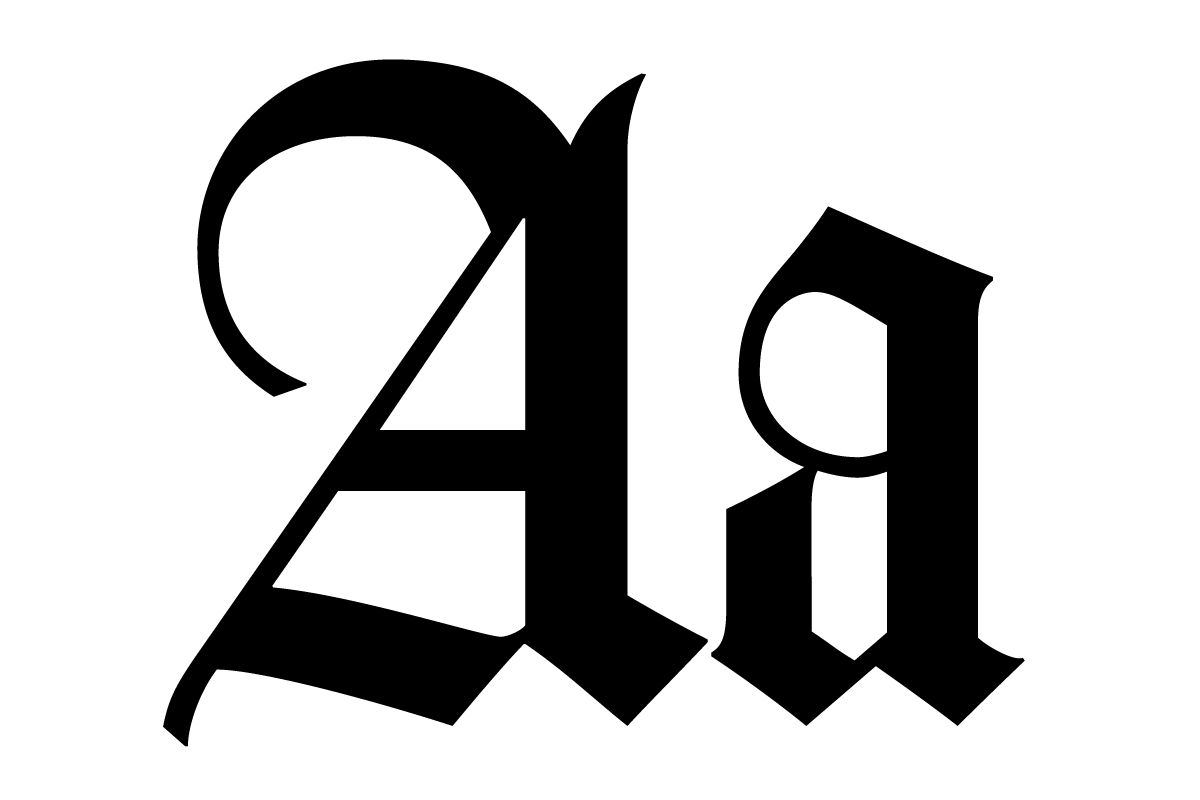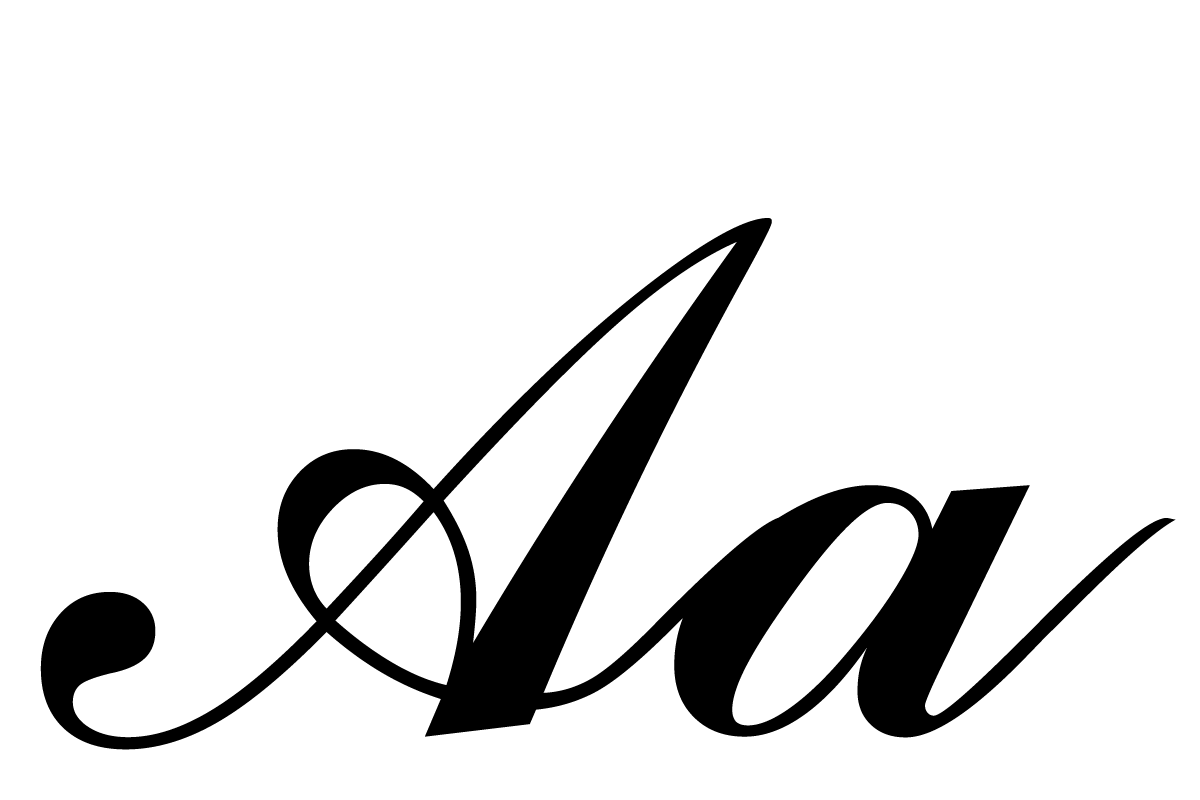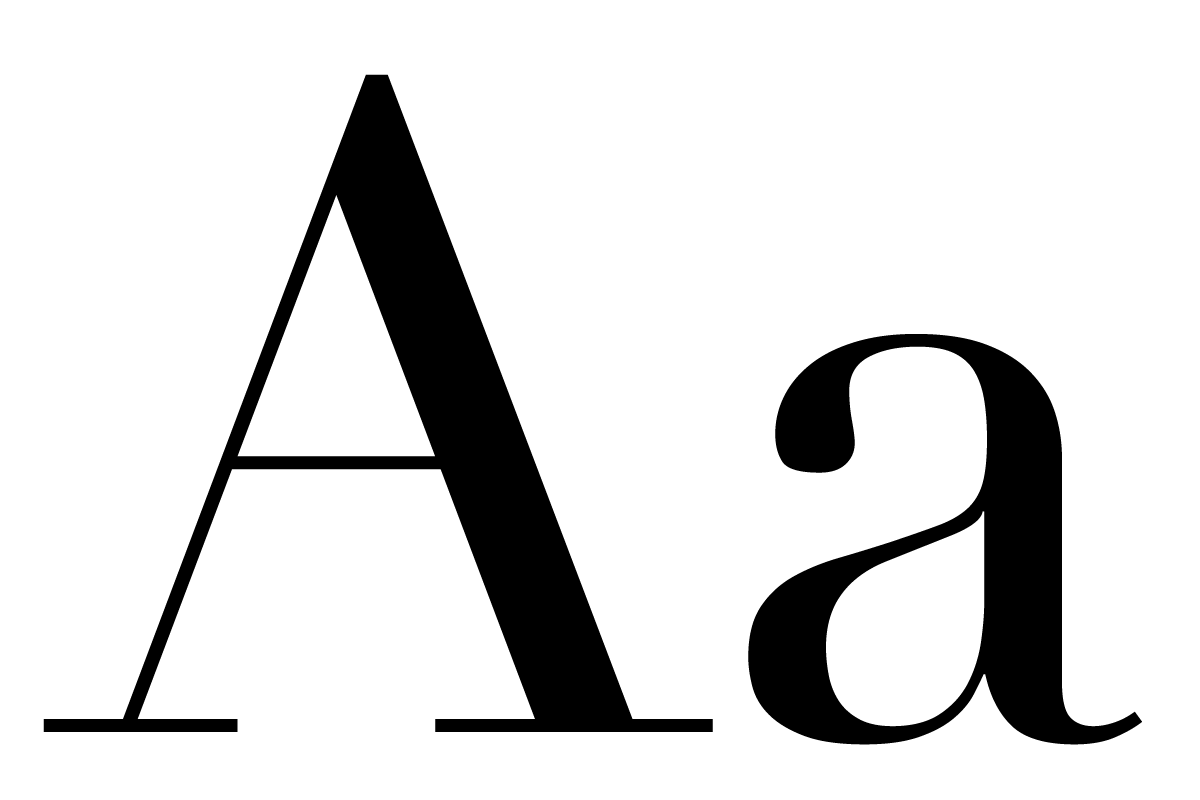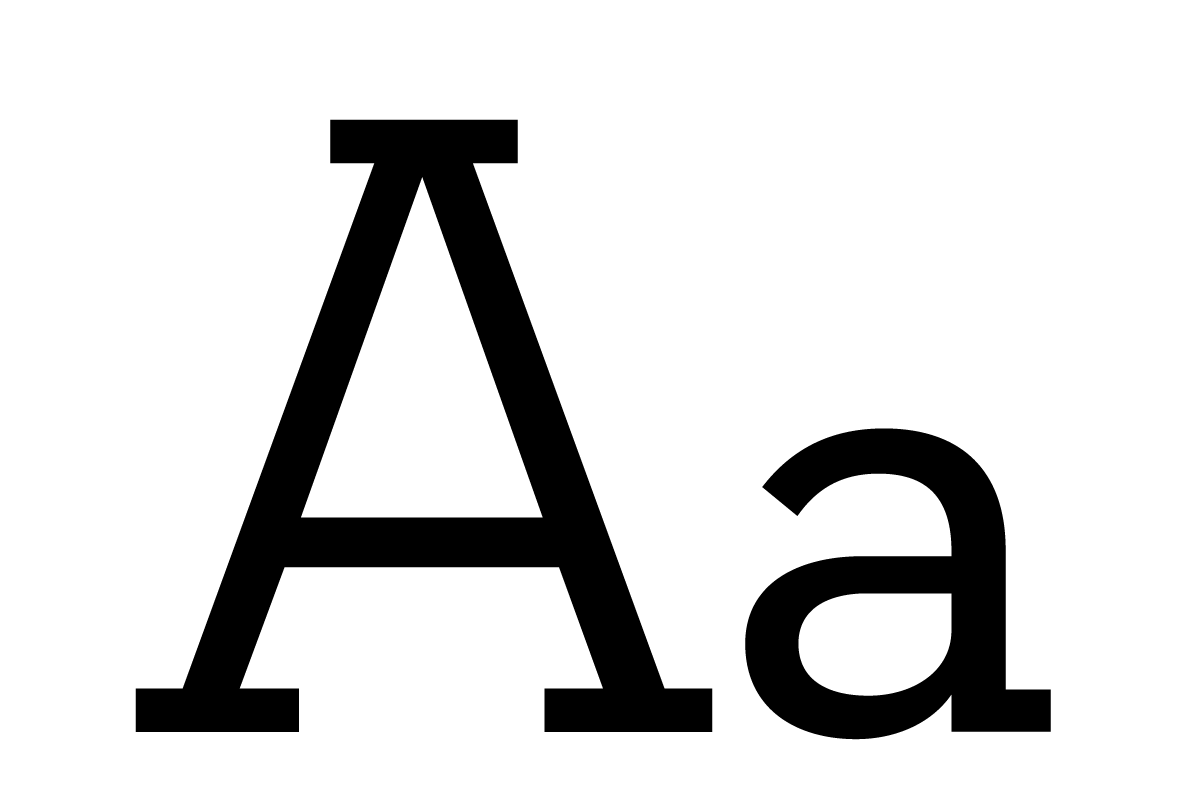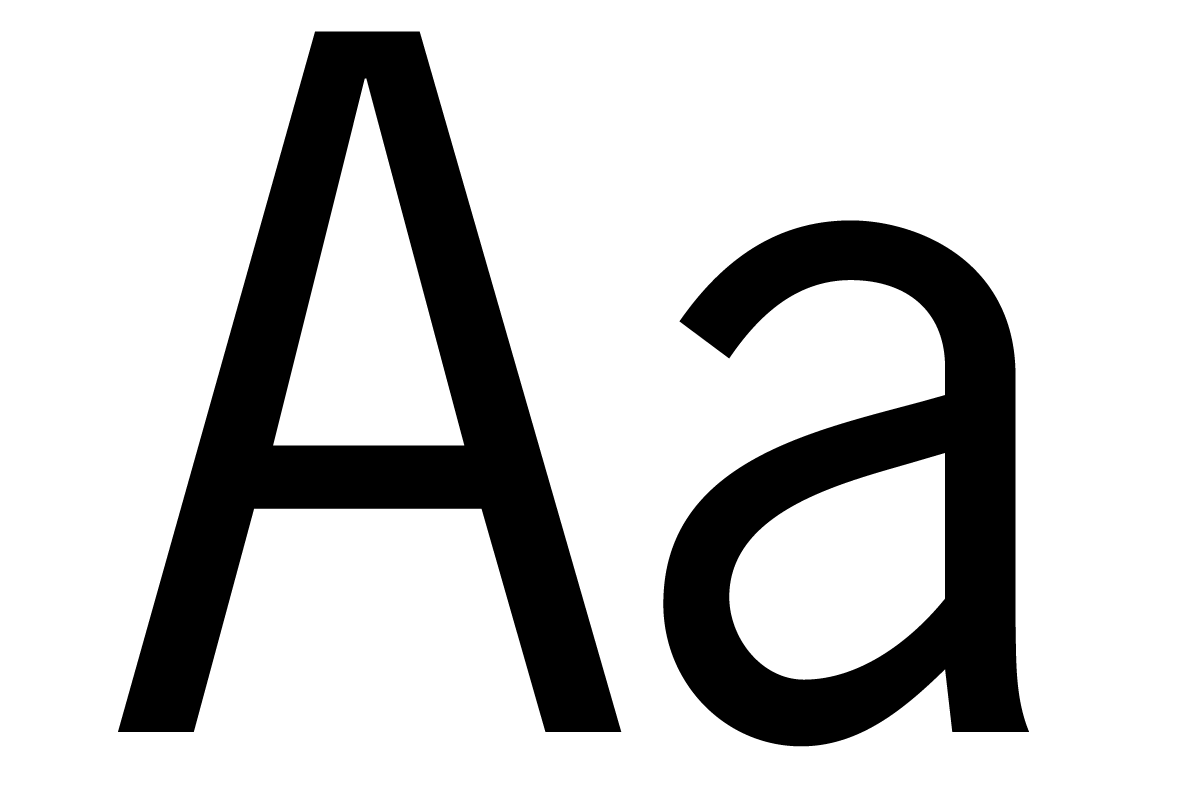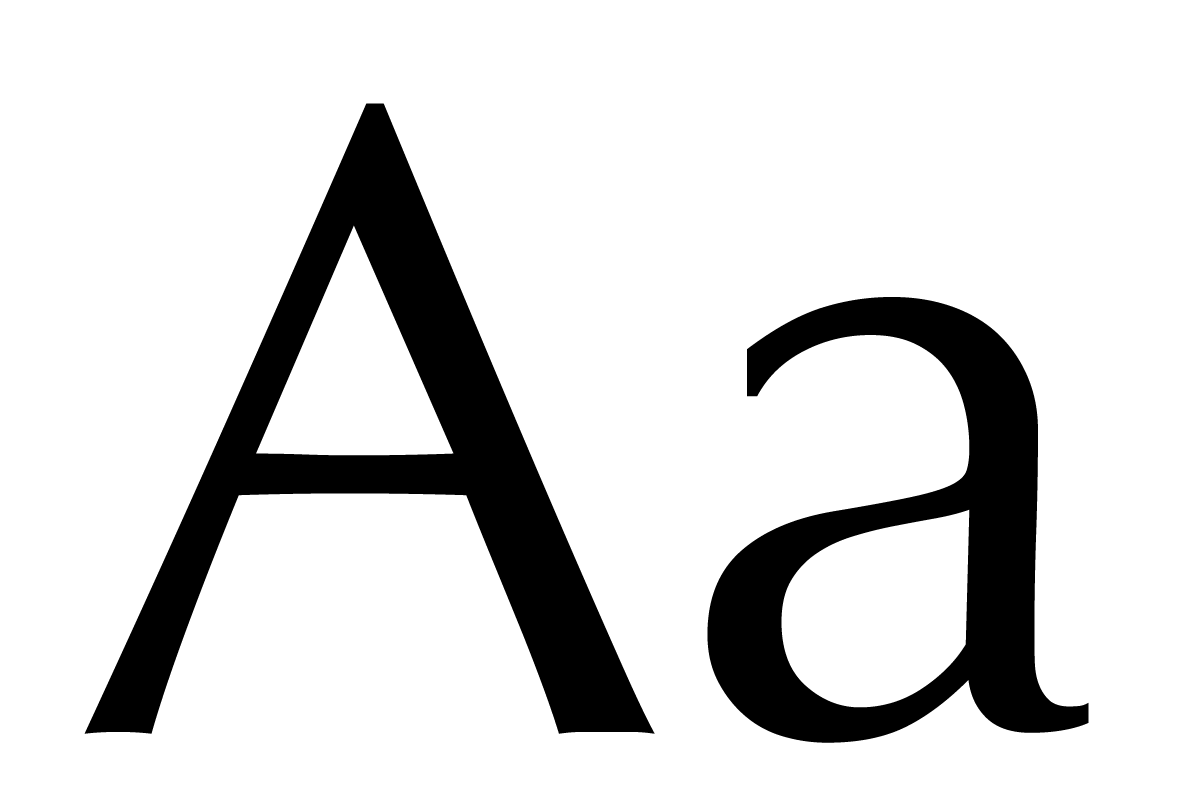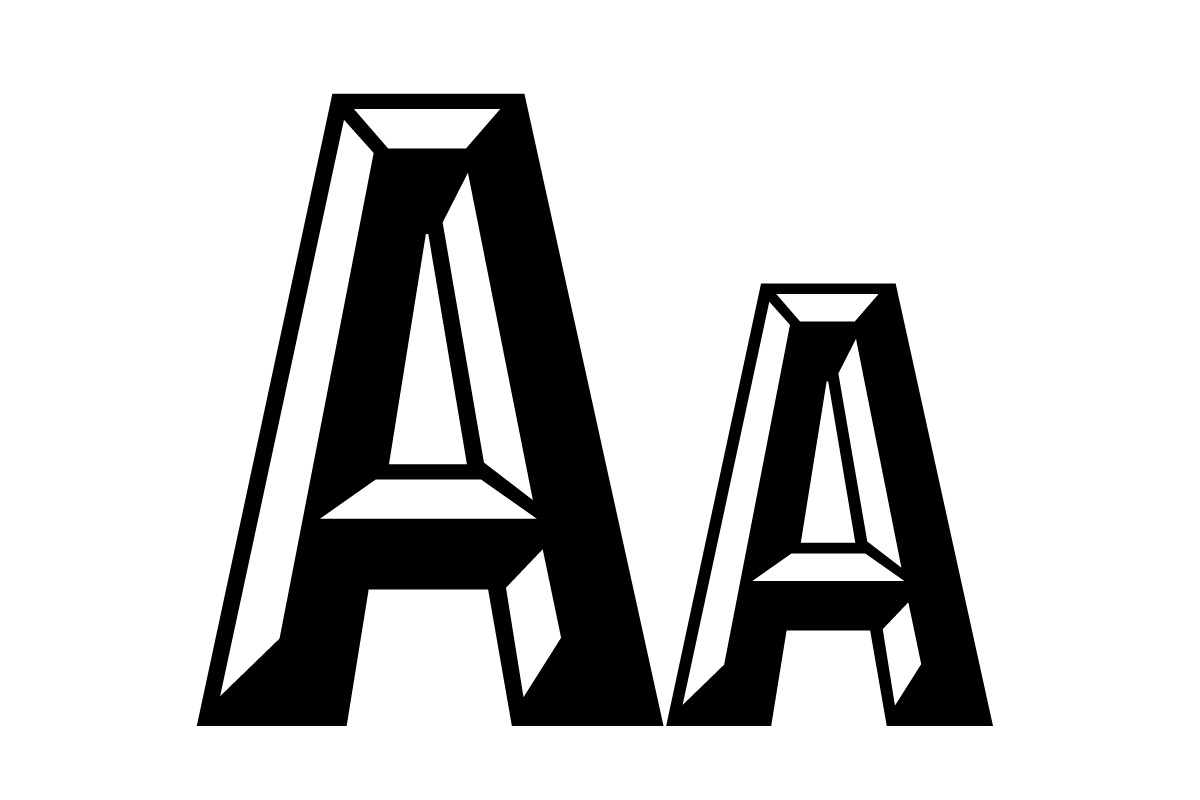
CLASSIFICATION
ここではフォントの分類について説明をしてゆきます。古典的なフォントや人気のフォントを除けば詳しい人でも名前の知らないフォントが山のようにあります。フォントは世界中の大小様々なファウンダリーから提供され、現在インターネット上で簡単に購入することができます。無数のフォントも基本的な分類を知ることで大まかな見え方の特徴を把握することができます。分類は学術的な分類や書体メーカーの独自のものなど統一的規格のようなものはありませんが、フォントの購入の際の分類やアプリケーションで基本的に使う一般的な分類を考えてサイト独自に行なっております。
Here we will explain the classification of fonts. Apart from classic and popular fonts, there are many fonts that even the most knowledgeable person does not know the names of. Fonts are available from foundries of all sizes all over the world and can be easily purchased on the Internet. The myriad of fonts can be roughly characterized in terms of appearance by knowing the basic classifications. Although there is no unified standard for font classification, such as an academic classification or a typeface manufacturer’s own, we have created our own classification system to provide a general classification that is basically used when purchasing fonts and in applications.
SERIFセリフ・ローマン
画線の末端に爪状のセリフがついた書体。ローマン体ともよばれ古代ローマでこの様式の大文字が確立し碑文などへと使われたことで長く西洋の歴史の中に存在してきました。印刷術の発明直後から活字として用いられ長い歴史の中で洗練され、そして、現在も利用されている最もスタンダードな字体です。通常、文芸作品などの出版物の本文はこの形式の書体が用いられています。由緒のある説得力のある字形もさることながら、セリフによる水平方向への力が目の運びを助けることで、紙媒体での安定した読みやすさを確保してくれるため特に好んで使われています。
A typeface with claw-shaped serifs at the ends of the strokes.Also known as Roman typeface, this style of capitalization was established in ancient Rome and has existed in Western history for a long time as it was used for inscriptions.It has been used as a typeface since shortly after the invention of printing and has been refined over its long history, and is still the most standard typeface in use today.This typeface is usually used for the text of literary works and other publications. Aside from its venerable and persuasive character form, It is particularly favored because the horizontal force of serifs helps the eye to carry the text, ensuring stable readability on paper.
OLD STYLE オールドスタイル
三角形状のセリフ(ブラケット)の処理と曲線部の有機的な形体が特徴。16世紀までの間に確立され使われており、曲線部にカリグラフィーからの名残が残る有機的な形体が人間の目に馴染み、由緒ある古典的な定番として、公文書や文芸作品からメニューに至るまで現在も幅広く使われています。
The triangular serif (bracket) process and the organic shape of the curves were established and used until the 16th century, and the organic shape of the curves, which still retains traces of calligraphy, is familiar to the human eye. It is still widely used today in everything from official documents and literary works to restaurant’s menus.
TRANSITION STYLE トランジション
オールドスタイルとモダンスタイルの中間的な特徴をもつ書体。オールドスタイルのもつ有機的な造形を残しながらも、細部の処理をより精巧に鋭い細さを持たせることで線のコントラストをもつ特徴がある。古典と近代の橋渡し的な時代にデザインされ幾何学的なアプローチの方向性をつけることになったことで過渡期(transition)と呼ばれている。
This typeface has characteristics that are in between the old style and the modern style. While retaining the organic shapes of the old style, the details are more carefully processed to create a sharp contrast of lines.It is called “transition” because it was designed in the period that bridged the gap between the classical and modern styles and set the direction of the geometric approach.
Modern Style モダンスタイル
セリフが直線で処理され縦線と横線のコントラスト強い特徴があるスタイル。紙や印刷機などの進化とともに、新たな形を試みた活字のデザイナーが銅版印刷などの美しいヘアラインを取り入れてより理想的な形体を求めて、より幾何学的なアプローチでデザインされた書体のスタイル。ニュースペーパーからマガジンまでモダンなメディアで幅広く使われています。
This style is characterized by straight serifs and a strong contrast between vertical and horizontal lines.This style of typeface designed by type designers who tried out new forms as paper and printing presses evolved, incorporating beautiful hairlines from copperplate printing and other methods.A style of typeface designed with a more geometric approach in search of a more ideal form. It is widely used in modern media from newsprint to magazines.
SANS SERIFサンセリフ
セリフの無い書体。フランス語で’sans’は「無い」の意味でセリフが無いという意味です。普段私たちが目にする機会の多い現代的な形体の書体です。スラブセリフやモダンスタイルの成功は、より純粋な、より幾何学的なアプローチへと傾きセリフを廃して合理的な形体へとたどり着きました。形体が簡素で、視認性が良く、同一形体の太さの展開など合理的でシステマティックな近代の需要にあう書体として様々な場面で多く用いられています。
A typeface without serifs. The French word ‘sans’ means ‘without serifs’.It is a typeface with a modern form that we usually see in our daily lives.The success of sans serifs and modern styles has tended toward a simpler, more geometric approach, eliminating serifs and arriving at a rational form. It is often used in a variety of situations as a typeface that meets the rational and systematic demands of modern times with its simplicity of form, good legibility, and the development of different weights.
Grotesque Sans/ Gothic グロテスク・ゴシック
19世紀から20世紀初頭にデザインされた初期のサンセリフ体のスタイル。モダンセリフやトラジションセリフの骨格の影響をうけ、看板製作の伝統などからも影響を受けている。硬く黒みが強い一方、不規則で少し甘いカーブや線幅の強弱に温かみが残る。
An early sans serif style designed in the 19th and early 20th centuries. It is influenced by the framework of modern serifs and transition serifs, as well as by the tradition of sign writing. hard and dark, it retains warmth in its irregular, slightly sweet curves and the intensity of the stroke width.
Neo Grotesque Sans ネオグロテスク
20世紀中盤にグロテスクをさらに合理的にデザインをし直し、より規則性を強めたスタイル。ストロークのコントラストを抑えることで直線部分が際立ち規則正しい印象が特徴。最もニュートラルな印象で使われる今日の基本的なサンセリフ。
The grotesque style of the mid-20th century was redesigned to be more rational and regular. It is characterized by a more regular impression, with the straight parts emphasized by a reduction in the contrast of the strokes. The basic sans serif used today with the most neutral impression.
Humanist Sans ヒューマニストサンズ
旧来のローマン体の骨格を持ち、カリグラフィー由来の特徴を残すことで有機的な形態を含んだサンセリフ。近代デザインの合理性への向きと人間由来の美意識を見事に調和するスタイル。サンセリフの中でも最も可読性に優れ本文に利用にも適している。
The sans serif has the skeleton of the old Roman typeface and contains organic forms by retaining calligraphic-derived features. This style is a perfect blend of the rational orientation of modern design and the human-derived aesthetic sense. It is the most readable of the sans serif styles and is suitable for use in body text.
Geometric Sans ジオメトリックサンズ
直線や円などの組み合わせを骨格に持ち幾何学的なアプローチのサンセリフ、バウハウスなどのモダンデザインの合理的な志向を背景に始まり、現代デザインに求められる視認性や合理性を満たす最も現代的なスタイル。
It began with the rational orientation of modern design, such as Bauhaus, which have a geometric approach with a framework of straight lines, circles, and other combinations,The most contemporary style that satisfies the visibility and rationality required in modern design.
SLABSERIF / EGYPTIANスラブセリフ・エジプシャン
誇張された線幅、直線的なセリフが特徴の書体。19世紀セリフ書体のモダンスタイルによるアプローチがセリフの形体に変化をもたらし、より直線的により太く単純化へデザインしてゆく方向があらわれました。それは工業化時代の始まりとともに広告告知などを目的とした安価な商業印刷物へ、キャッチーでインパクトのある書体デザインが求められ、その結果セリフを極端に太く持つスタイルや極端な線幅のスタイルなどが生まれました。
This typeface is characterized by exaggerated line widths and straight serifs.The modern approach to serif typefaces in the 19th century brought about a change in the serif style, and a trend toward simpler, straighter, and thicker designs emerged. With the beginning of the industrial age, typefaces with catchy and impactful designs were demanded for inexpensive commercial printed materials for advertising, resulting in styles with extremely thick serifs and extreme line widths.
Geometric Slab ジオメトリックスラブ
ジオメトリックスラブは、直線的なセリフをもち幾何学的、合理的なアプローチで設計されたスタイルです。視認性にすぐれ本文からディスプレイ用途まで幅広く使われます。
Geometric slab is a style designed with linear serifs and a geometric, streamlined approach. It has excellent visibility and is used in a wide range of applications, from text to display purposes.
Clarendon/Ionic クラレンドン/イオニック
クラレンドン/イオニックはスラブセリフの中でも、ブラケットセリフやボールターミナルなどの特徴をもち、19世紀の無骨さが残る、幾何学と有機的な曲線のバランスが特徴のスタイル。
Clarendon/Ionic is a style of slab serifs that has features such as bracket serifs and ball terminals, and is characterized by a balance of geometry and organic curves that retain the ruggedness of the 19th century.
SCRIPTスクリプト
筆記体を活字へと置き換えたスクリプト書体。その他の書体とは異なり、続け書きによる前後の文字がつながるように工夫され、流れるような手書きの筆記体を再現したデザイン。ヘアラインの美しいカッパープレート(銅版印刷)やサインペインターなどのブラシを再現したものなど様々なテイストが存在する。
This is a script typeface that replaces the writing style with type. Unlike other typefaces, this typeface has a design feature that reproduces the flowing handwritten style of writing, with the letters before and after the typeface being made to connect by continued writing. Various tastes exist, including those that reproduce beautiful hairline copperplate (copperplate printing) and signature painters’ brushes.
Capperplate Script カッパープレートスクリプト
極細のヘアラインと滑らかな太いストロークが特徴のスクリプト書体。イングリッシュラウンドハンドとも呼ばれ、カリグラフィー由来の筆記体です。イタリック体をより早く描くための続き文字で線幅が滑らかに変化するリズムが印象的です。
A script typeface with an ultra-fine hairline and smooth, thick strokes. Also called English Roundhand, it is a writing style derived from calligraphy. The rhythm of the smoothly changing line widths is impressive.
Brush Script ブラシスクリプト
ブラシを使って描かれたような特徴を持つの書体。看板職人や手描きの値札などのブラシを使って書いていたスクリプト書体を模した書体で、線幅や線の抜きに特徴がある。アップストロークとダウンストロークにコントラストがあるものや、丸筆や平筆を使った特徴を出したものなどがあります。
A typeface that has the look like drawn with a brush. This typeface is modeled after the script typefaces used by sign makers and hand-painted price tags, which were written using brushes, and has characteristics in line width and line removal. Some have contrasting upstrokes and downstrokes, and others are characterized by the use of round or flat brushes.
BLACK LETTERブラックレター
フラットペンの平面のストロークが多く黒味の強い角ばった書体。ヨーロッパで中世にキリスト教の写本などに使われており、ゴシックの建築との形体の関連性もある。印刷術を発明したグーテンベルグが最初に作った書体はこのブラックレター。
An square typeface with many flat pen strokes and a strong black tinge. It was used in Europe in the Middle Ages for Christian manuscripts and has a stylistic connection with Gothic architecture. Gutenberg, who invented the art of printing, first created this typeface Black letter.
Displayディスプレイ
ディスプレイタイプはポスターやパッケージなどの短い言葉を目立たせる目的で作られたタイプフェイスです。広告や見出しなどの本文を前提としないアイキャッチを目的として作られることで、様々な表現が存在していています。
Display typeface is a typeface created for the purpose of making short words stand out on posters, packages, etc. Various expressions exist, as they are created for the purpose of eye-catching without assuming the text of the advertisement or headline.
Inline インライン
文字のストローク部分を中心線を入れることで、一つの線をアウトラインとインラインに分けて複雑な線表現を行う装飾方法です。
This is a decorative method that divides a single line into outline and inline by adding a center line to the stroke of the letter to create a complex line expression.
Shaded シェイデッド
文字のストロークを角度をつけて均等にずらした影(シェイド)部分を作ることで立体的な表現をおこなう装飾方法です。
This is a method of decoration that creates a three-dimensional expression by shading the strokes of letters at an angle to create evenly displaced shaded areas.
Decorative デコラティブ
文字のストローク部分などにイラストレーティブな装飾を施したものです。ウッドタイプなどでは複雑な表現を盛り込んだものが数多くあります。
Illustrative ornamentation is applied to the strokes of the letters. Many wood types incorporate intricate expressions.
Engraved エングレーブド
文字のストローク部分をエングレービング(彫金)の技法で浮き彫りをするように立体的に表現する装飾方法です。
This is a method of decoration in which the strokes of letters are expressed three-dimensionally in relief using engraving techniques.
3D スリーディー
文字のストローク部分や文字形自体を立体的に表現した装飾。ベベルなどの幾何学的な立体表現やイラストレーディブな表現などがあります。
A decoration in which the strokes of letters or the letterforms themselves are expressed three-dimensionally. There are geometric three-dimensional expressions such as bevels and illustrative expressions.
TUSCAN トスカン
ウッドタイプなどによく用いられるスタイルで、枝分かれしたセリフやストロークに装飾的なアクセントがつくのが特徴です。
This style is often used in wood type and other styles, and is characterized by decorative accents on branching serifs and strokes.